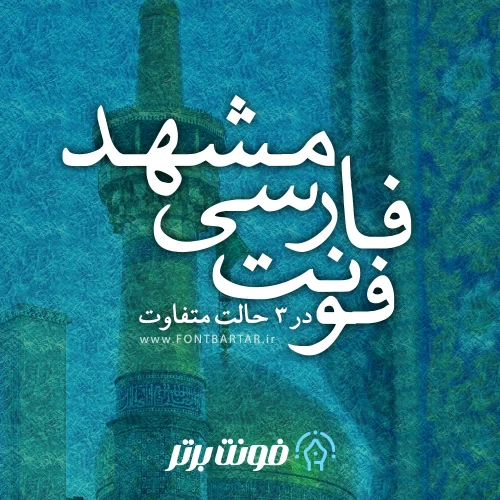
دانلود فونت مشهد
دانلود فونت فارسی بی مشهد ، فونت فارسی کلاسیک با ساختار نوستالژی مناسب برای استفاده در عناوین و طول متن برای استفاده های عمومی ، در سه وزن مختلف ، کاملا خوانا از دسته فونت های فارسی سری بی (برنا رایانه) که می توانید هم اکنون اخرین نسخه فونت فارسی مشهد را از فونت برتر بصورت رایگان دانلود کنید.
فونت مشهد:
- دارای 3 استایل متفاوت
- کیفیت بالای طراحی
- مناسب استفاده در طراحی های خاص و زیبا